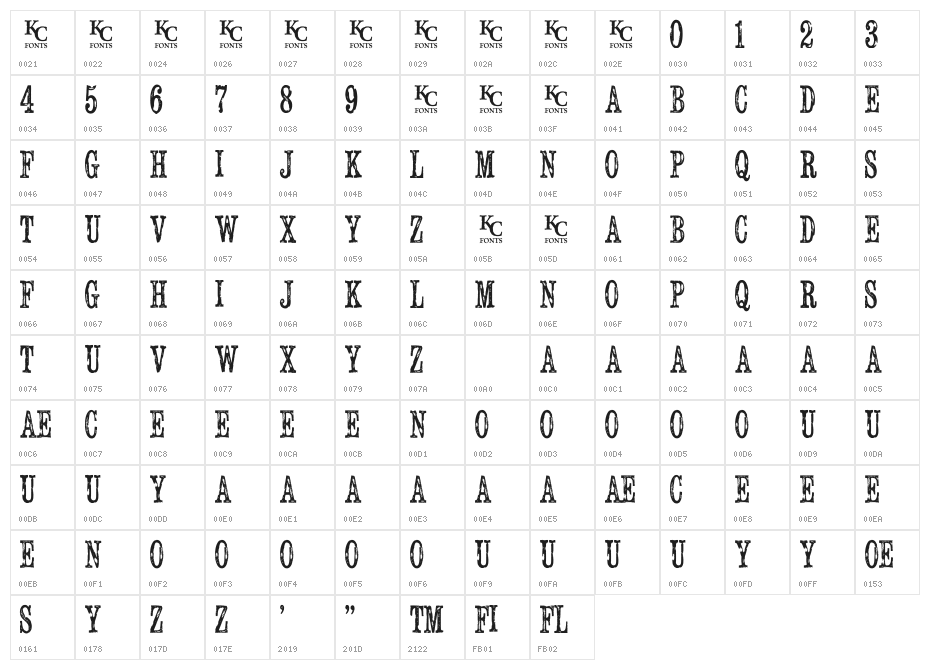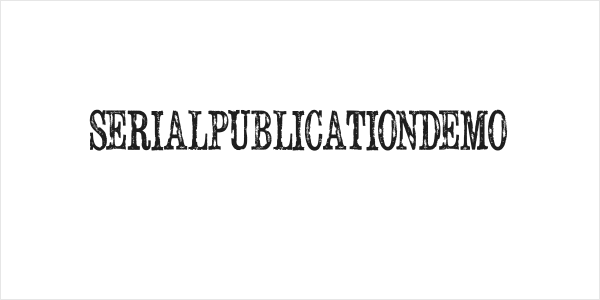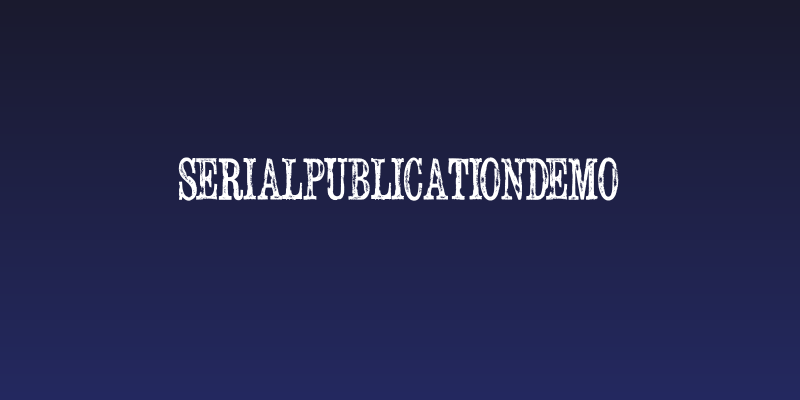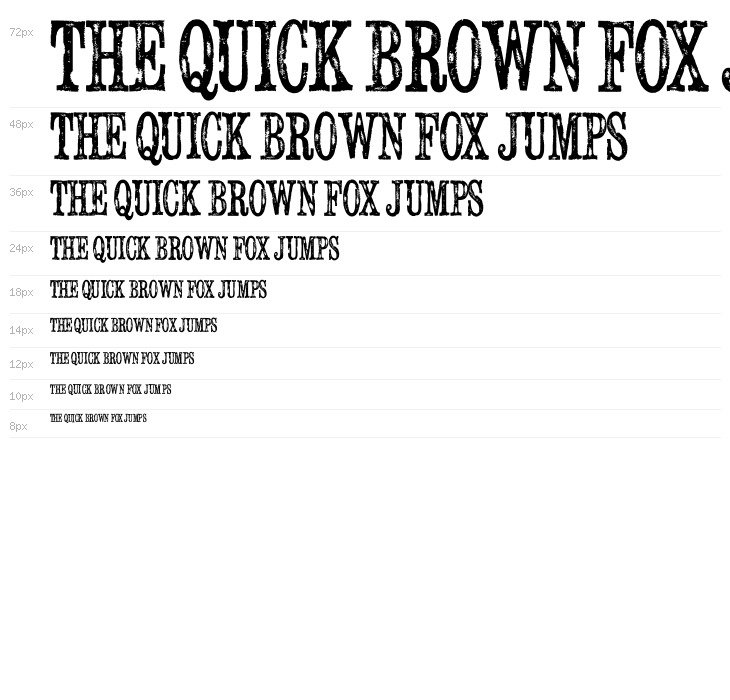
SerialPublicationDemo Font
✎ Distorted Eroded
| Progetti proposti | Ideal for vintage posters, retro-themed branding, rustic product packaging, and creative headlines. |